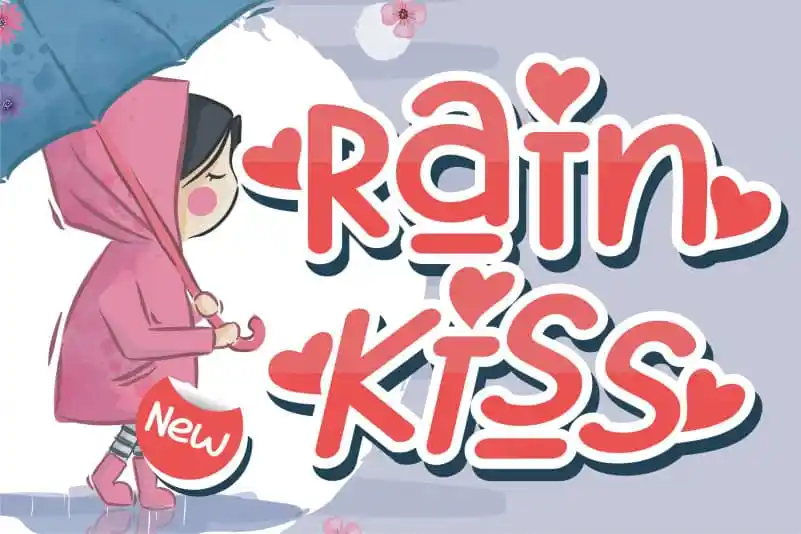
Rain Kiss Display Font – Fonte Grátis
Rain Kiss Display Font
A fonte Rain Kiss Display Font é uma escolha ideal para quem procura algo divertido e grosso no seu design visual. Esta fonte casual e simples pode ser usada em diversas ideias de decoração, especialmente se você estiver trabalhando com temas infantis. O designer letterenastudios trouxe esse estilo único para aqueles que desejam um toque alegre em seus projetos criativos. A combinação de uma tipografia elegante e um colorido vibrante faz dessa fonte um complemento perfeito para criações infantis, especialmente quando você incorpora tons mais vivos. Seja para decorar bonecas ou até mesmo para criar arte impressa para uma festa de criança, Rain Kiss é a escolha certa. Esta fonte oferece um toque especial que tornará qualquer projeto visual não apenas agradável de olho, mas também muito divertido e criativo.